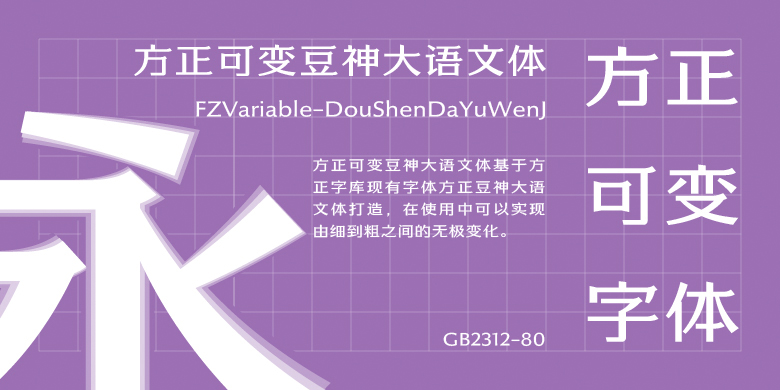
正可變豆神大語文體字體支持文字粗細(xì)無級調(diào)節(jié),設(shè)計(jì)師通過調(diào)整字重軸(Weight)的變化,可以實(shí)現(xiàn)字形的平滑連續(xù)的細(xì)微調(diào)整,滿足不同版式的設(shè)計(jì)需求。 方正豆神大語文體是為豆神教育科技(北京)股份有限公司旗下品牌“豆神大語文”而設(shè)計(jì)的定制字體。本字體以豆神大語文logo為字體創(chuàng)作基礎(chǔ),經(jīng)過取舍優(yōu)化延展設(shè)計(jì)成全套字庫。其字形扁方、重心平穩(wěn),體現(xiàn)教育企業(yè)給人的親和與信任感。中文筆形略帶宋意,筆畫間滲透著中華傳統(tǒng)文化的傳承,正與中華傳統(tǒng)學(xué)科——語文的特性相契合。橫畫尾部向上翹起,象征企業(yè)長遠(yuǎn)發(fā)展,同時也表達(dá)對萬千學(xué)子蒸蒸日上的美好祝愿。豆神大語文體共有4個字重,可以適應(yīng)標(biāo)題、文本等不同的使用需求。西文與中文匹配設(shè)計(jì),字形偏扁,采用半襯線形式,筆畫末端弧度與中文相呼應(yīng)。力求在保持拉丁文書寫邏輯的基礎(chǔ)上,視覺上與中文相統(tǒng)一。